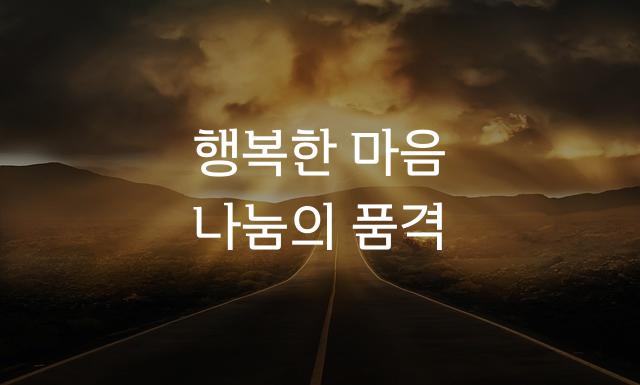
완주대둔산체는 장식체와 둥근 고딕의 조화로움을 특징으로 하는 한국어 폰트입니다. 가로로 긴 문자의 형태가 세련된 인상을 주며, 따뜻하고 부드러운 감성을 전달합니다.
완주대둔산체은(는)
기본 고딕, 둥근 스타일, 두꺼운 스타일, 장식 스타일, 감성적인, 부드러움, 복실복실, 별모양/패턴 계열의 생김새를 가지고 있으며
출판 디자인, 출판물 제목 등에서 자주 활용되며, 효과적인 메시지 전달에 적합합니다.
이 폰트는 출판/미디어, 문화/예술 분야에 잘 어울리며,
전통적, 클래식한 느낌을 담고 있는 것이 특징입니다.